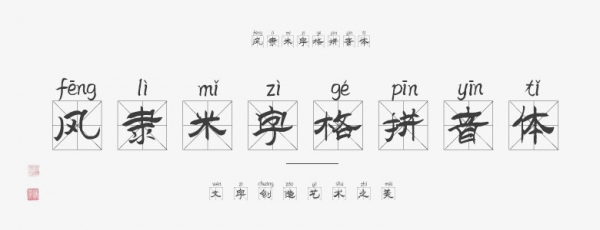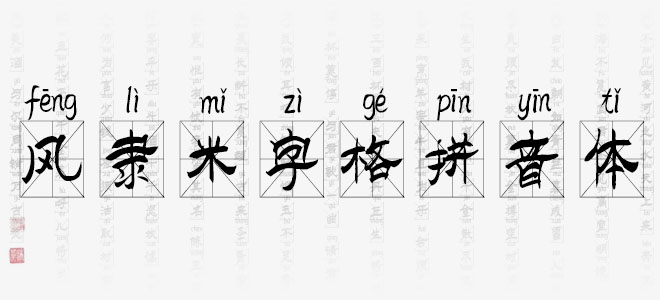
風(fēng)隸米字格拼音體是一款賞心悅目的藝術(shù)字體,具有強(qiáng)烈的視覺沖擊力。適用于海報(bào)、電商海報(bào)設(shè)計(jì)、店鋪設(shè)計(jì)、標(biāo)志設(shè)計(jì)、字體設(shè)計(jì)等領(lǐng)域。
風(fēng)隸米字格拼音體